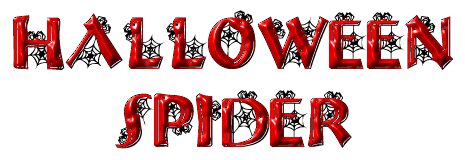
Halloween Spider autorstwa Melle Derieppe Claude to bezpłatny, dekoracyjny krój pisma na Halloween, który zamienia każde słowo w nagłówek opleciony pajęczyną. Grube, czarne litery wypełnione są jedwabistymi pajęczynami i drobnymi stworzeniami wyglądającymi zza rogów, co nadaje tekstowi zabawny, nieco upiorny, a zarazem uroczy charakter. Wyraziste kształty pozostają czytelne nawet przy dużej liczbie detali, dzięki czemu Twoje halloweenskie przekazy zyskują teatralny klimat bez efektu chaosu.
Dzięki Halloween Spider Twoje tytuły przykują uwagę na zaproszeniach na imprezy, plakatach domów strachów, torbach na słodycze, grafikach do mediów społecznościowych, materiałach szkolnych czy banerach okolicznościowych. Ten bezpłatny font najlepiej prezentuje się w większych rozmiarach, gdzie pajęczyny i pająki mogą naprawdę „rozpełznąć się” na stronie. Połącz go z prostym, bezszeryfowym krojem w głównym tekście i postaw na jaskrawe pomarańcze, fiolety oraz zgniłą zieleń, aby każdy nagłówek krzyczał „Halloween”.
Halloween Spider